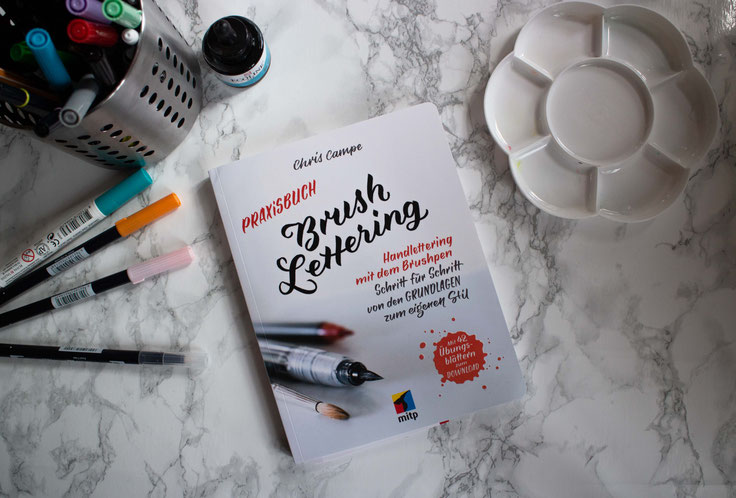
[PR-Sample/Werbung] Ich hatte die Möglichkeit einen Blick in das neue Buch "Praxisbuch Brush Letteirng - Handlettering mit dem Brush Pen* - Schritt für Schritt von den Grundlagen zum eigenen Stil" von Chris Campe zu werfen, welches im mitp Verlag erschienen ist. Für wen dieses Brushlettering Buch geeignet ist und ob ich es euch empfehlen kann, erfahrt in meiner Buchvorstellung.
Um was geht's?
Wie der Titel schon sagt geht es um das Erlernen von Handlettering mit Fokus auf Brushlettering. Von den Grundlagen, bis hin zum eigenen Stil ist sehr viel Wissen in diesem 224 seitigem Werk vorhanden.
Das Buch ist unterteilt in vier Kapitel: Vorbereiten, Anfangen, Vertiefen und Anwenden. Die beiden ersten Kapitel sind vor allem für Anfänger interessant.
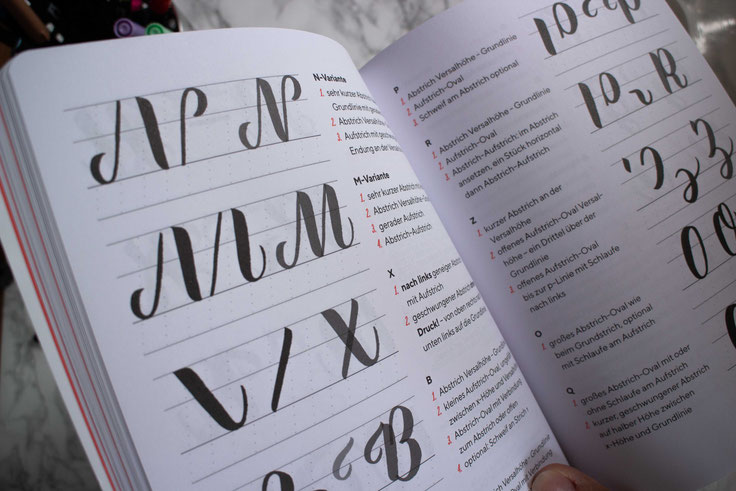
Im ersten Teil geht es um die Vorbereitungen, also zum Beispiel welche Stifte und Materialien ihr benötigt, aber auch um Begriffe der Typografie. Im Kapitel Anfangen geht es dann endlich los - man fängt mit Aufwärmübungen an und setzt dann Schritt für Schritt einzelne Buchstaben zusammen. Dafür nimmt sich das Buch sehr viel Zeit.
Doch auch als Fortgeschrittene könnt ihr noch viel mitnehmen.
Denn in Kapiteln Vertiefen und Anwenden geht um das Erlernen verschiedener Schriften, das gezielte Einsetzen von Farbe, Formen und Schatten und wie man aus einem Layout ein fertiges Handlettering erstellen kann.
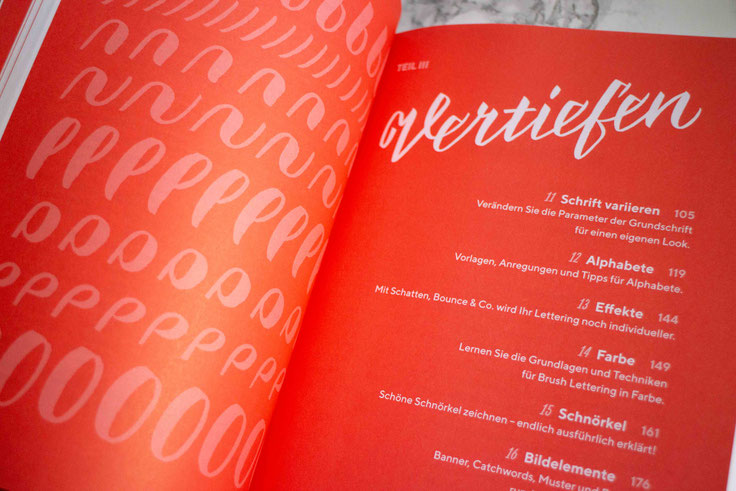
Wer hat das Buch geschrieben?
Autorin ist Chris Campe, auch bekannt als All Thing Letters. Als studierte Kommunikationsdesignerin besitzt sie viel Hintergrundwissen über Typografie und Gestaltungsrichtlichtlinien. Dies merkt man dem Buch auch an.
Was unterscheidet es von anderen Handlettering Büchern?
Der Umfang! Im Gegensatz zu vielen anderen Handlettering Büchern gibt es hier fundiertes Wissen und jede Menge Hintergrundinfos und Tipps. Es hat viele Beispiele, jedoch sind diese nicht so groß abgebildet, wie in manch anderen Handlettering Büchern. Durch dieses Buch muss man sich arbeiten. Es gibt viele Textpassagen, die jedoch gut strukturiert und immer wieder durch Beispiele unterbrochen werden.
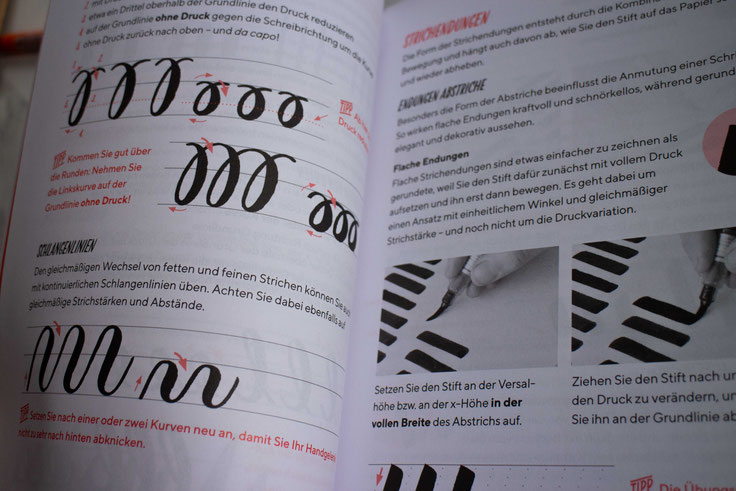
Hier bekommst du kein Fast Food serviert - in Chris Campe Buch gehst du (bildlich gesprochen) die Zutaten einkaufen, verarbeitest sie, kochst und zauberst dir selbst daraus ein 4 Gänge Menü.
Dabei kannst du dir aber auch nur die Vorspeise herauspicken, oder nur das Dessert, dies kannst du je nach Wissenstand selbst entscheiden.
Und das macht es gerade auch so interessant für Fortgeschrittene. Denn auch für Fortgeschrittene sind die schwierigeren Techniken wie zum Beispiel Bounce Lettering oder das Anwenden von Schnörkeln super erklärt.
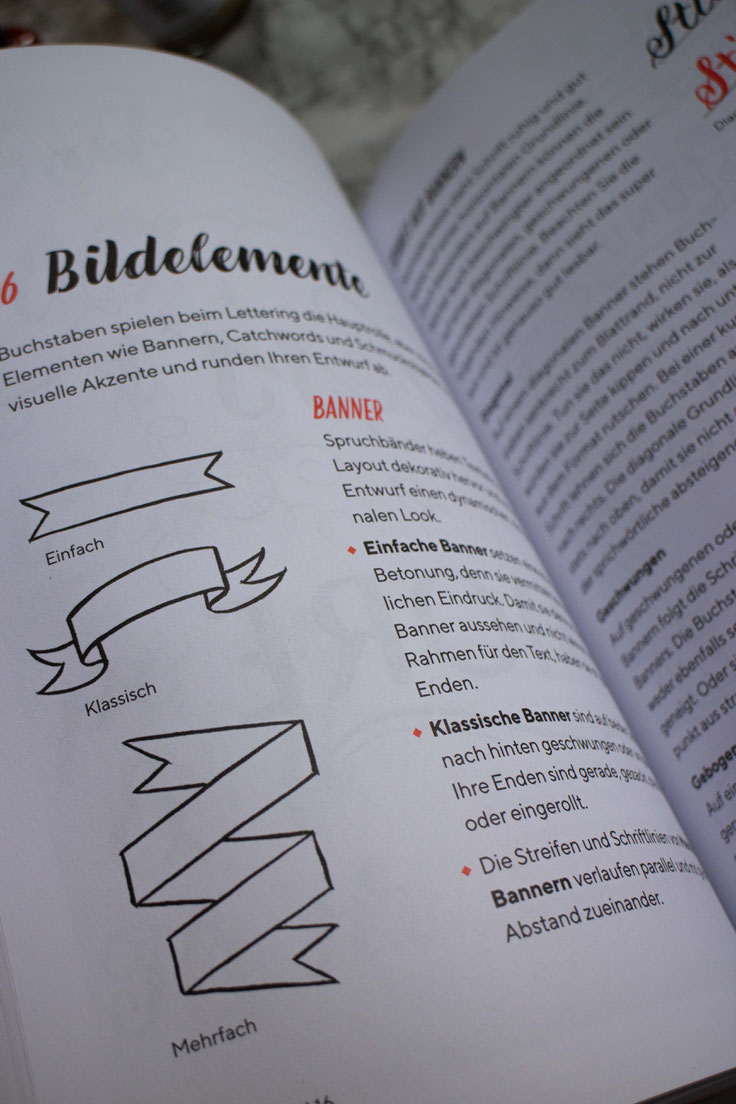
Für wen ist das Buch geeignet?
Ich empfehle dieses Buch für Anfänger und Fortgeschrittene gleichermaßen, die tief in die Theorie von Handlettering und Typografie eintauchen möchten. Mit diesem Buch wird man sein Wissen auf jeden Fall erweitern können und erhält zusätzlich jede Menge Praxistipps.